OpenType 格式
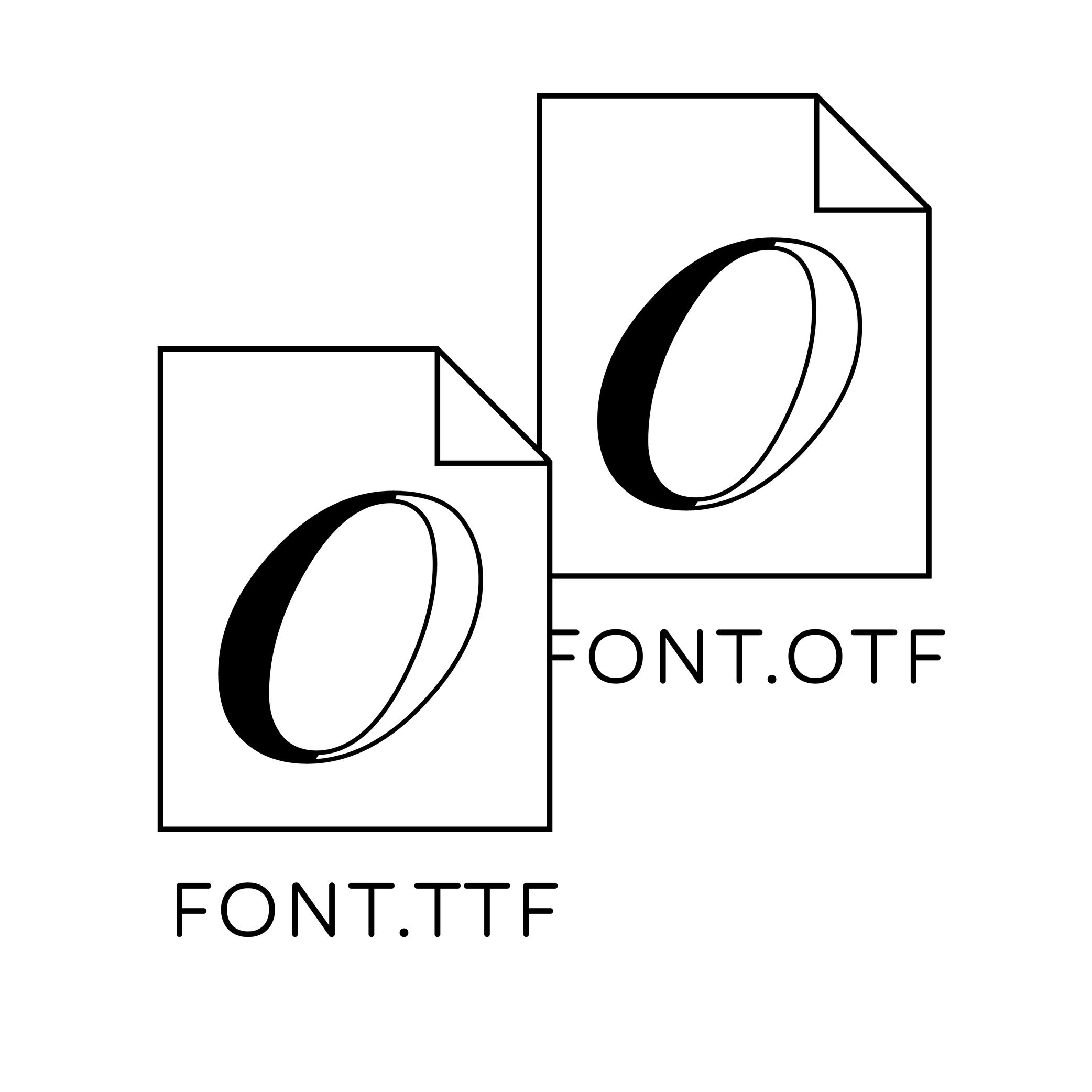
OpenType 是一种数字字体文件格式,由 Adobe 和微软于 1996 年创建。它主要是为印刷媒体上的字体而开发的,目前仍在不断发展中。
OpenType 字体文件在单个文件中包含字体样式的所有数据,从字形的造型和参数到称为 OpenType 特征的附加样式集。与其他字体格式相比,OpenType 的字形容量更大(多达 65000 个字符!)。
扩展